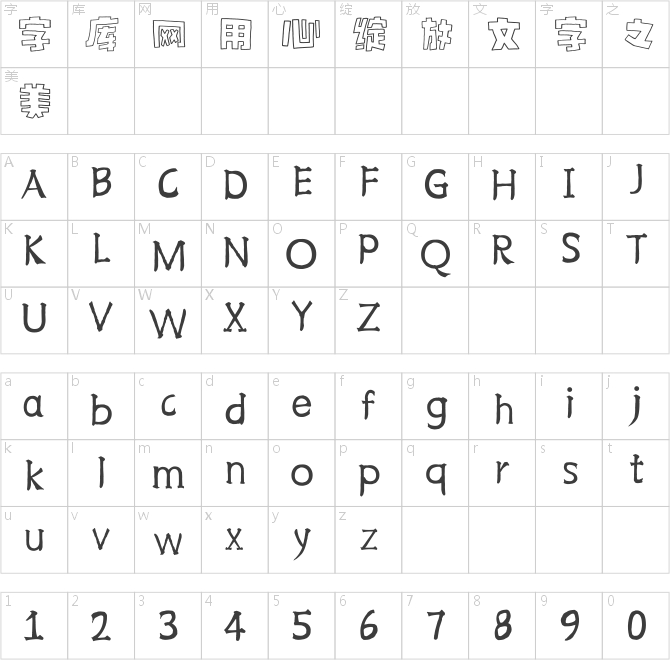
姥姥說媒韓艾璇小艾雙鉤簡體 詳情頁
姥姥說媒韓艾璇小艾雙鉤簡體字體下載小艾雙鉤簡體
小艾雙鉤簡體是一款逗趣可愛、動感活潑的創(chuàng)意美術(shù)標(biāo)題字。它的字形變化多樣,筆畫掏空,粗細(xì)對比強(qiáng)烈,組合起來富有節(jié)奏感。的字形多變,依據(jù)字體結(jié)構(gòu)而呈現(xiàn)出或長或方的節(jié)奏變化,十分俏皮可愛。